게임 유튜브에 많이 쓰이는 무료 폰트 10개
게임 유튜브는 한눈에 감정이 보여야 합니다. 공략 영상은 선명하게, 하이라이트 영상은 과감하게 보이는 폰트가 유리합니다.
빠르게 고르는 기준
- 게임 영상은 한눈에 감정이 보여야 하므로 획이 굵고 콘트라스트가 강한 폰트가 유리합니다.
- 공략 영상은 과장된 폰트보다 읽기 쉬운 고딕 계열이 더 오래 갑니다.
- 하이라이트·밈 영상은 제목용 폰트와 자막용 폰트를 분리하면 화면이 덜 어수선합니다.
1. 블랙 한 산스
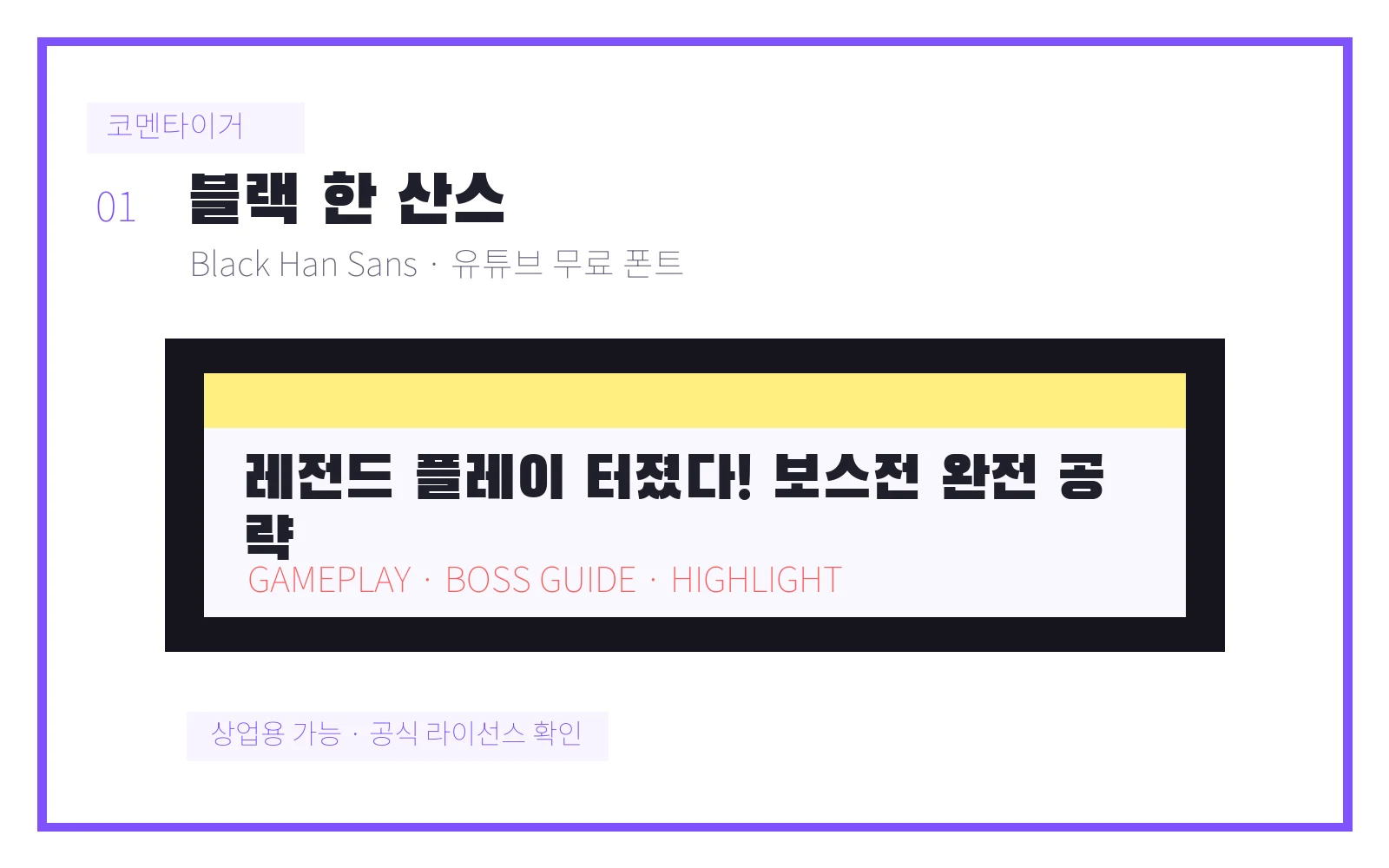
- 추천 용도: 강한 타격감이 있어 하이라이트 썸네일 제목에 좋습니다.
2. 도현
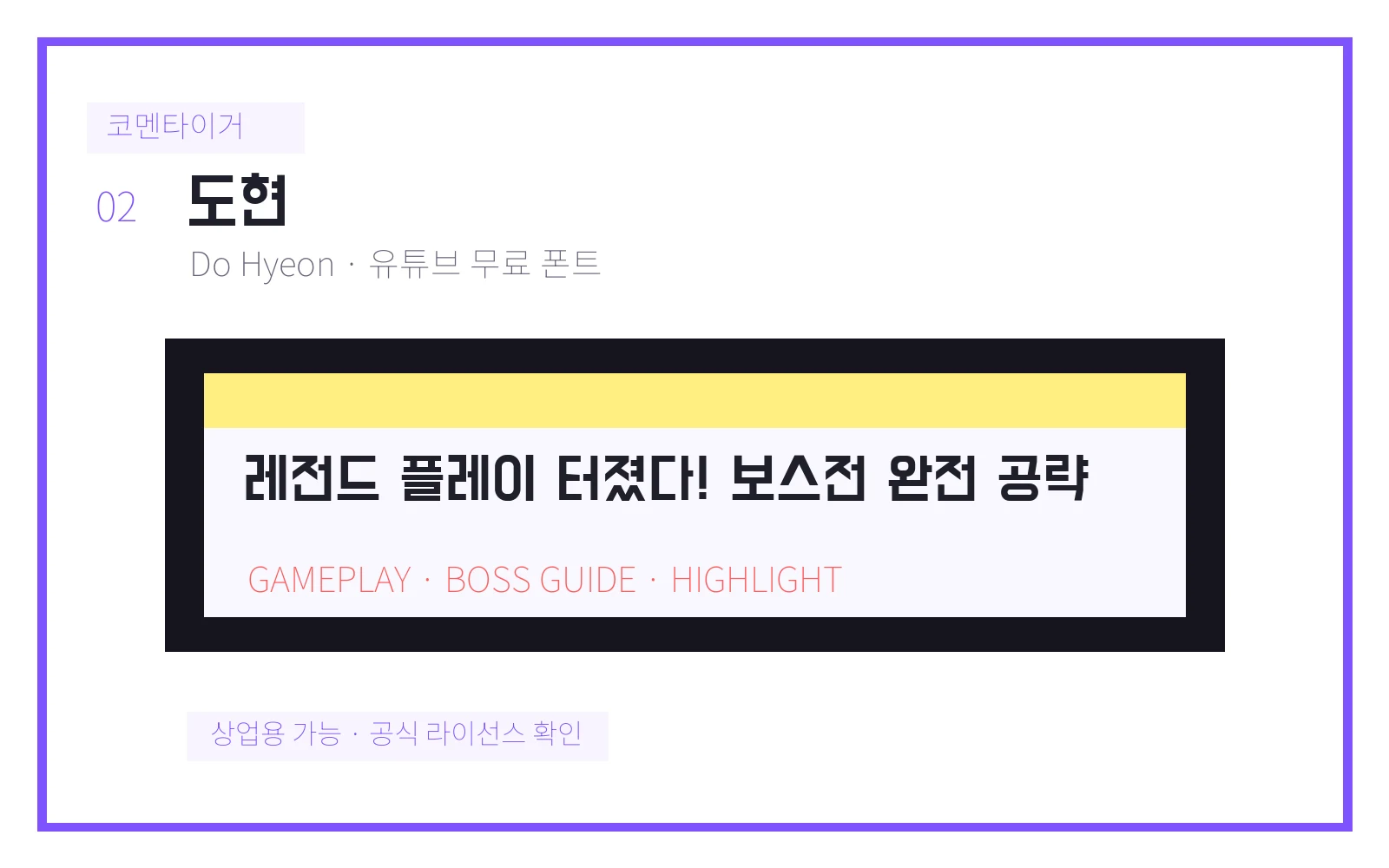
- 추천 용도: 공략, 리뷰, 티어표처럼 정보형 게임 영상에 잘 맞습니다.
3. 구기
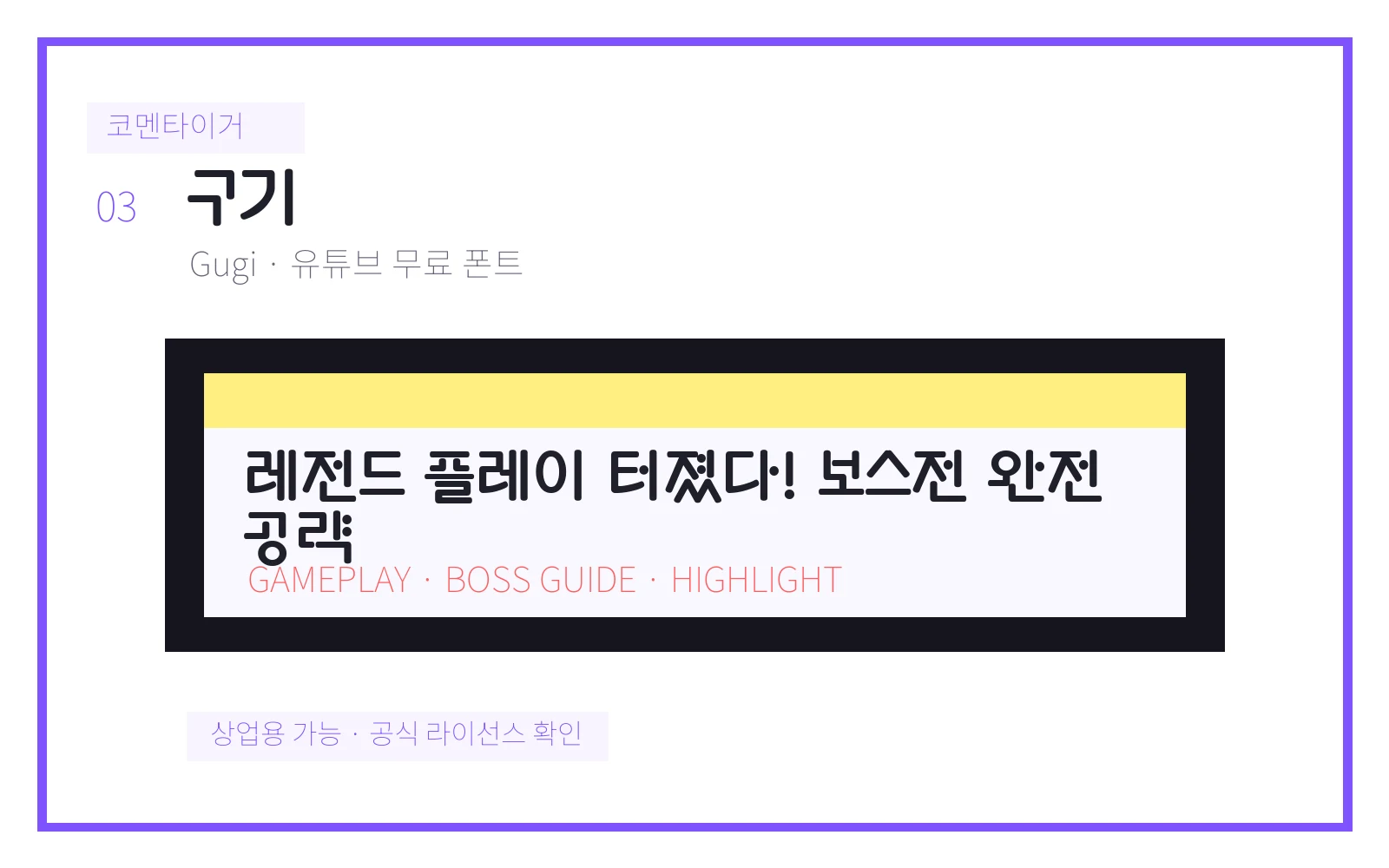
- 추천 용도: 게임 UI 같은 개성이 있어 포인트 문구에 쓰기 좋습니다.
4. 베이글 팻 원
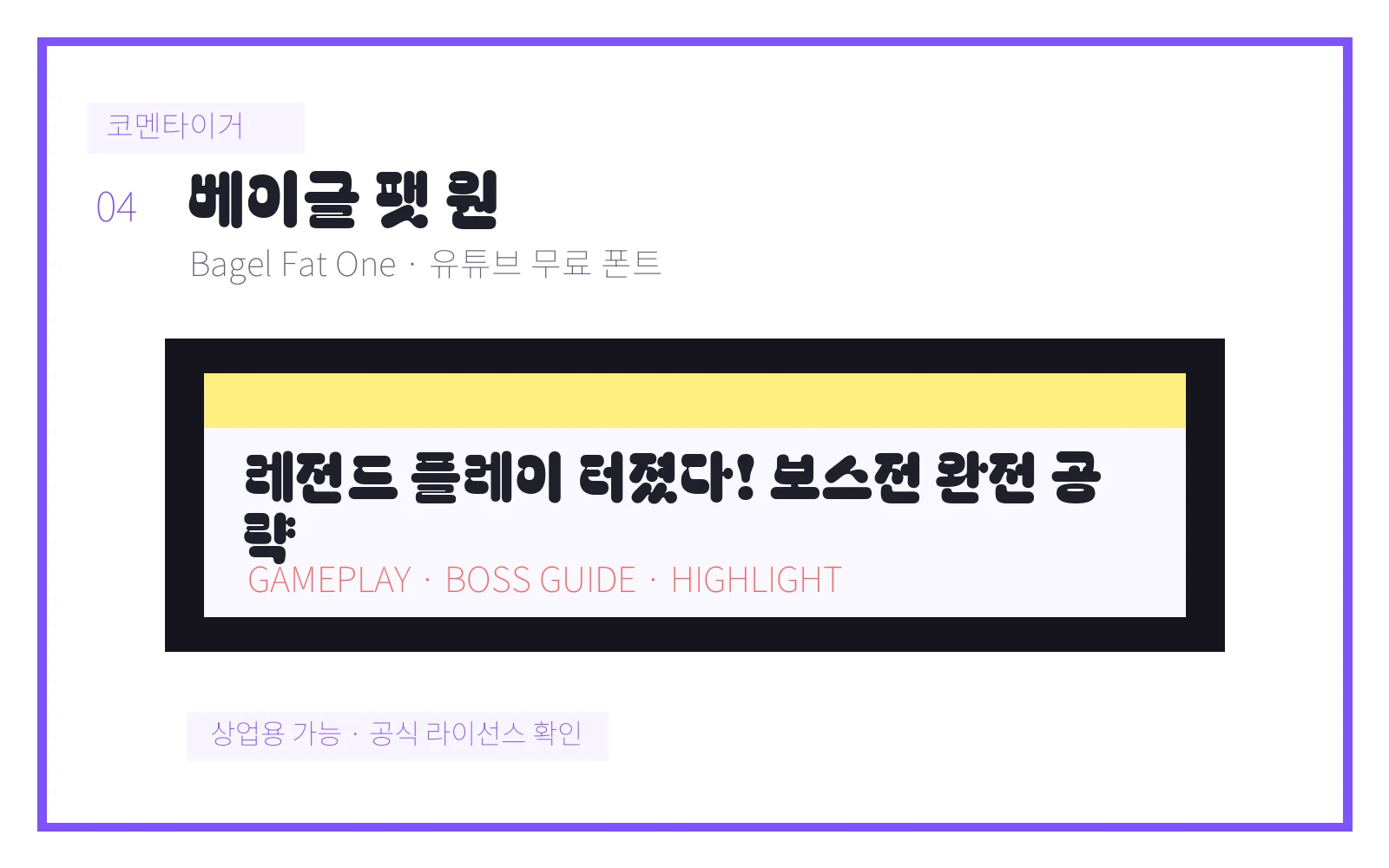
- 추천 용도: 캐주얼 게임이나 예능형 게임 영상에 어울립니다.
5. 동글
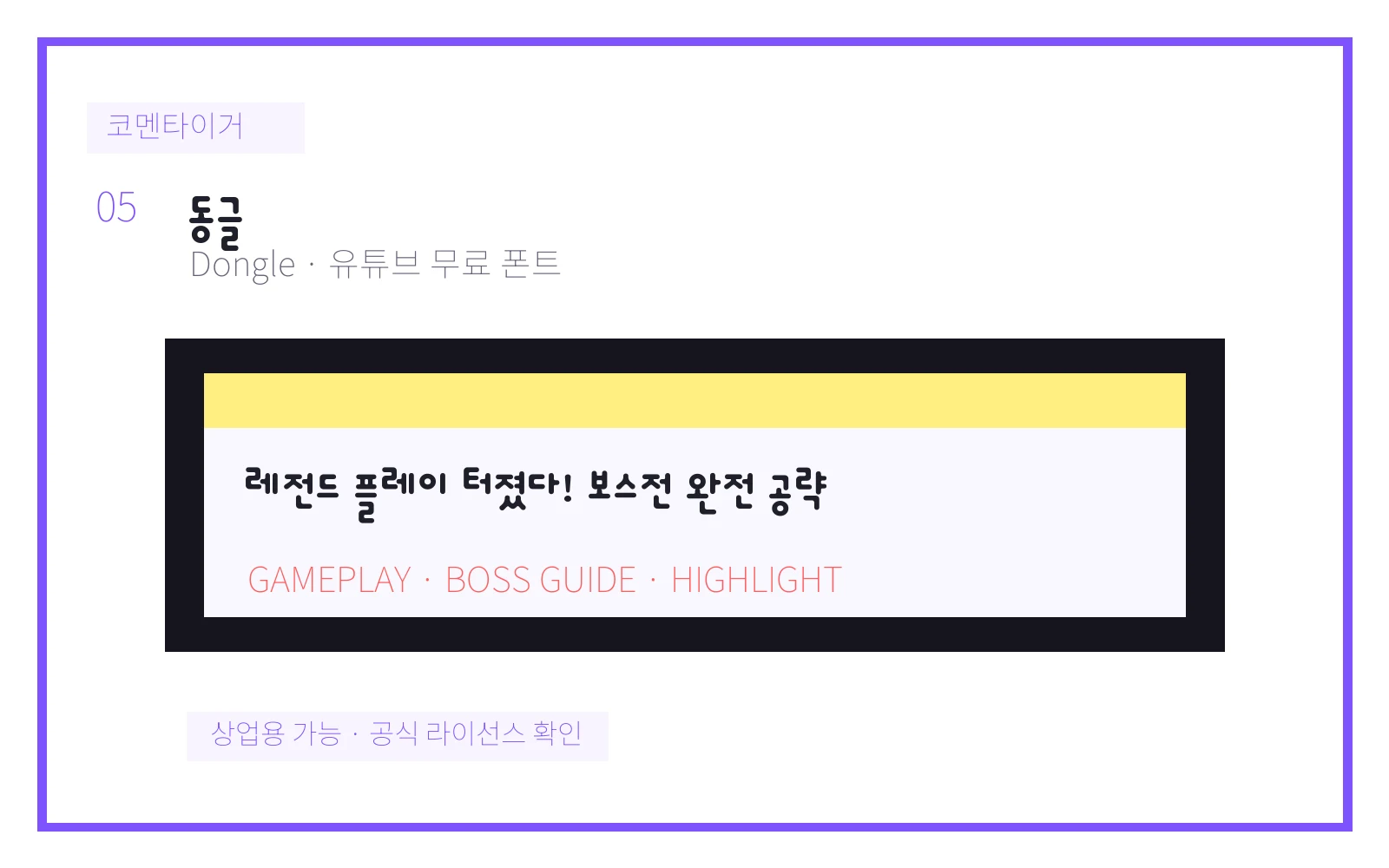
- 추천 용도: 큼직한 쇼츠 자막이나 리액션 문구에 쓰기 편합니다.
6. 주아
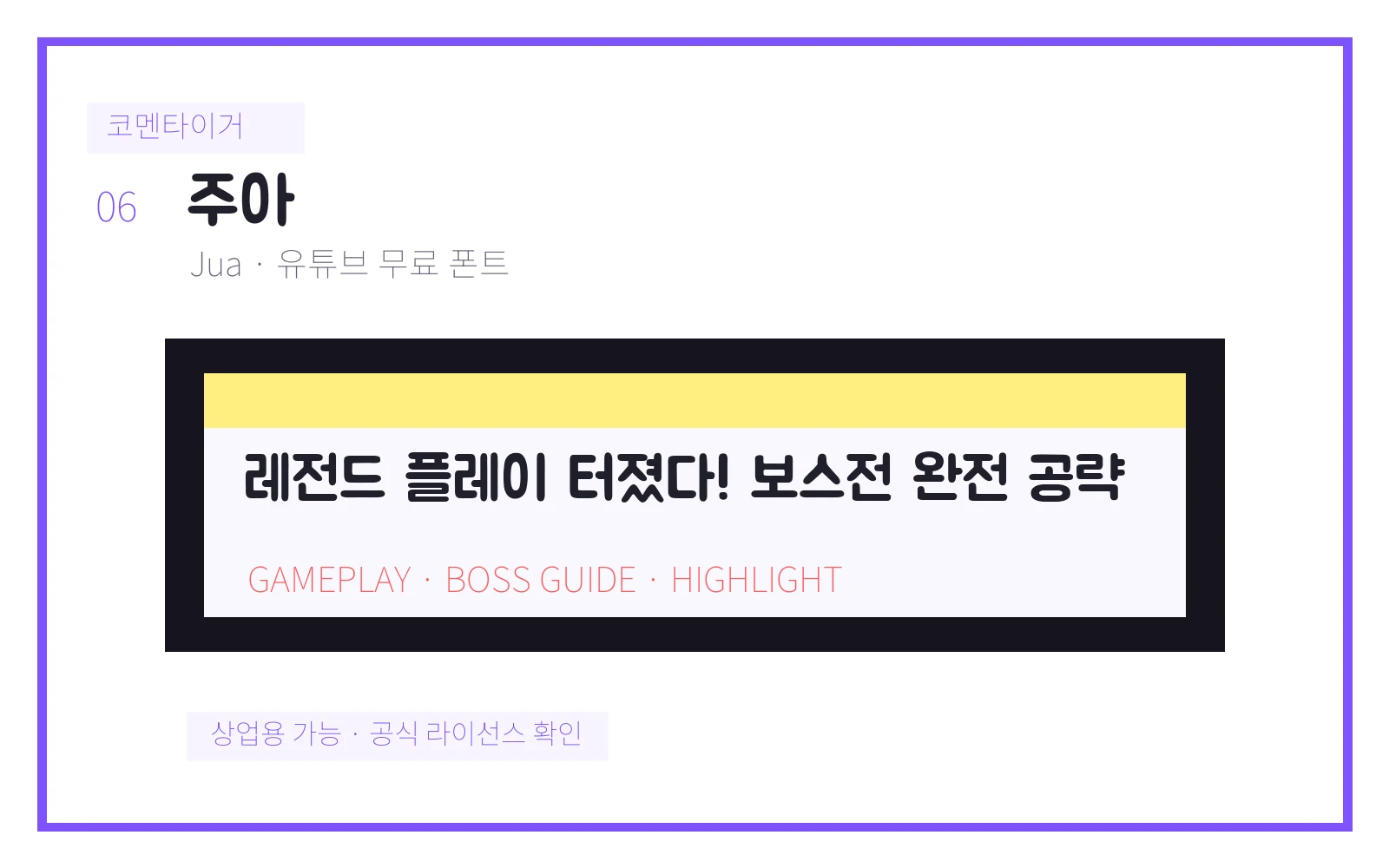
- 추천 용도: 친근한 인상이라 마인크래프트, 로블록스류 영상에도 무난합니다.
7. 독도
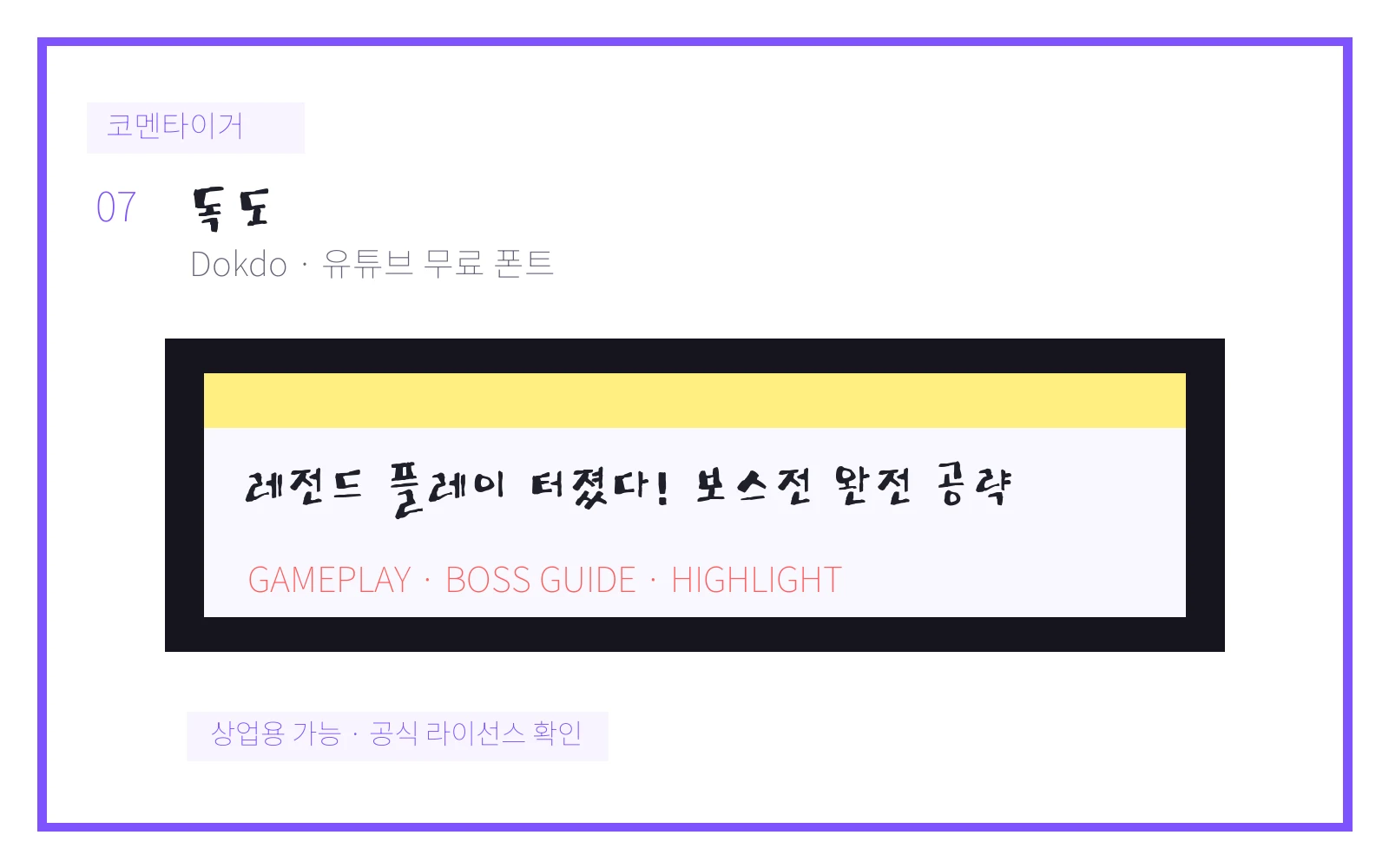
- 추천 용도: 거칠고 튀는 느낌이라 분노, 실패, 반전 문구에 잘 맞습니다.
8. 이스트 씨 독도
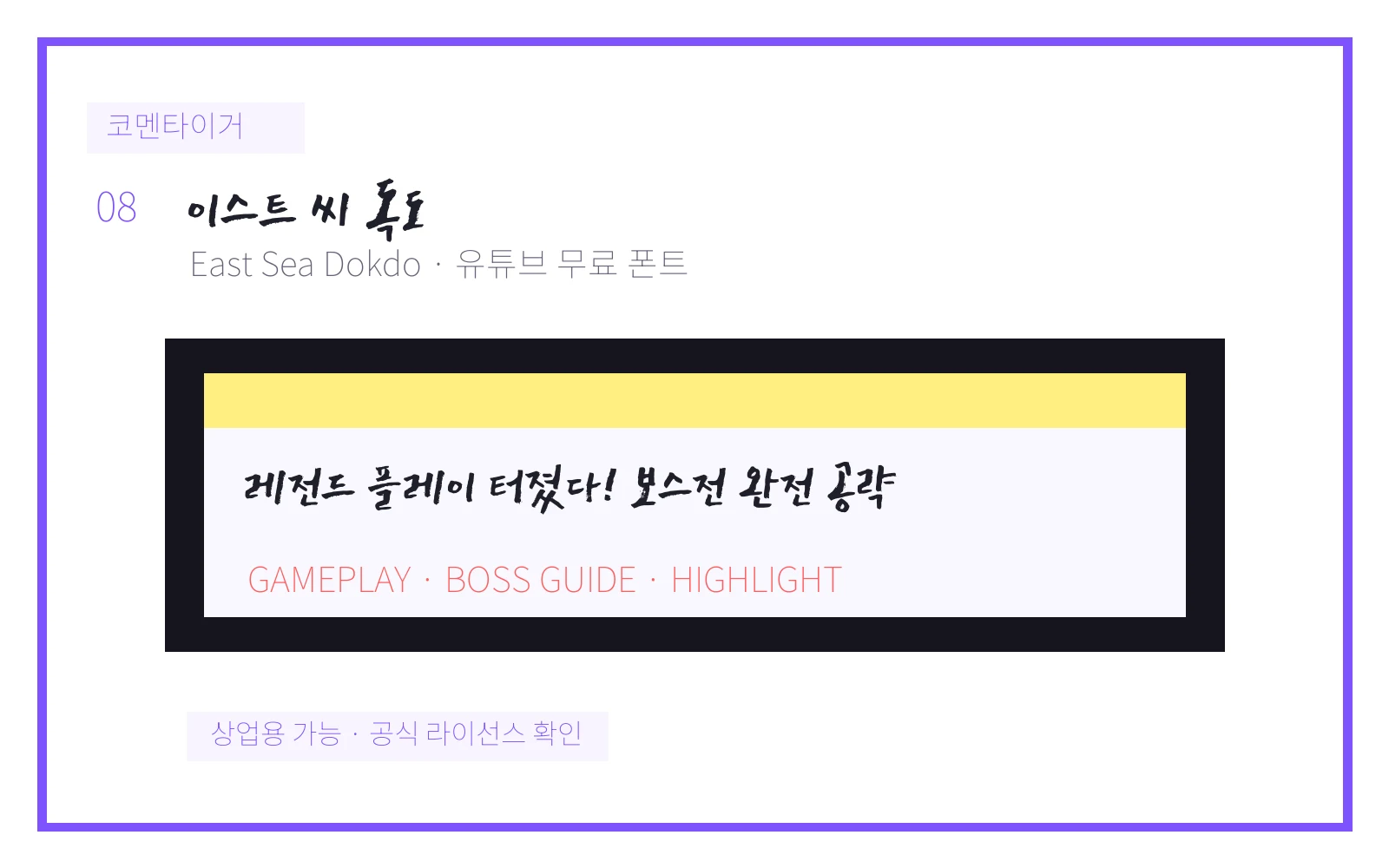
- 추천 용도: 강한 손맛이 있어 액션 게임 썸네일에 개성을 줍니다.
9. 키랑 해랑
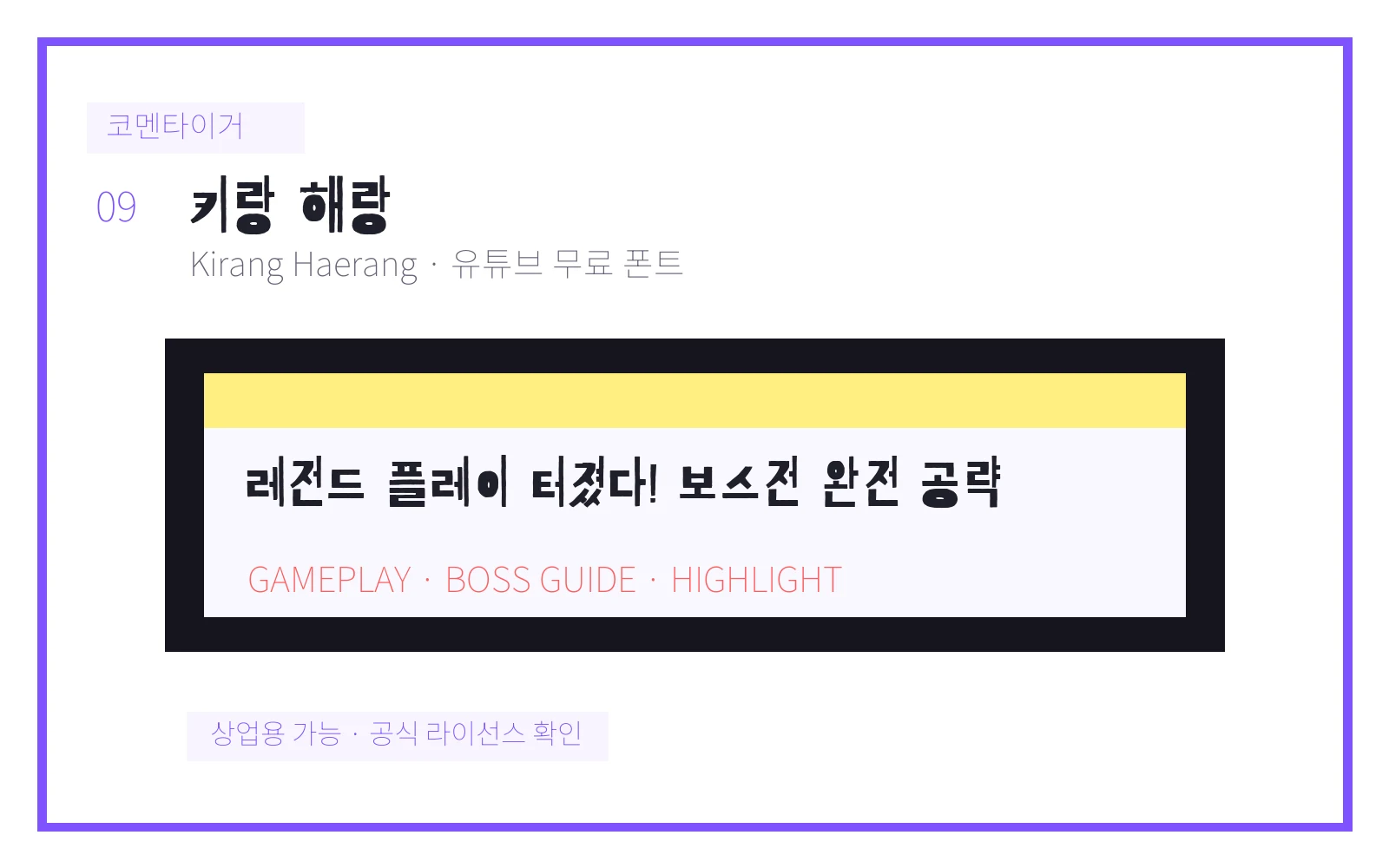
- 추천 용도: 장난스럽고 과장된 느낌이 있어 예능형 게임 자막에 좋습니다.
10. 함렛
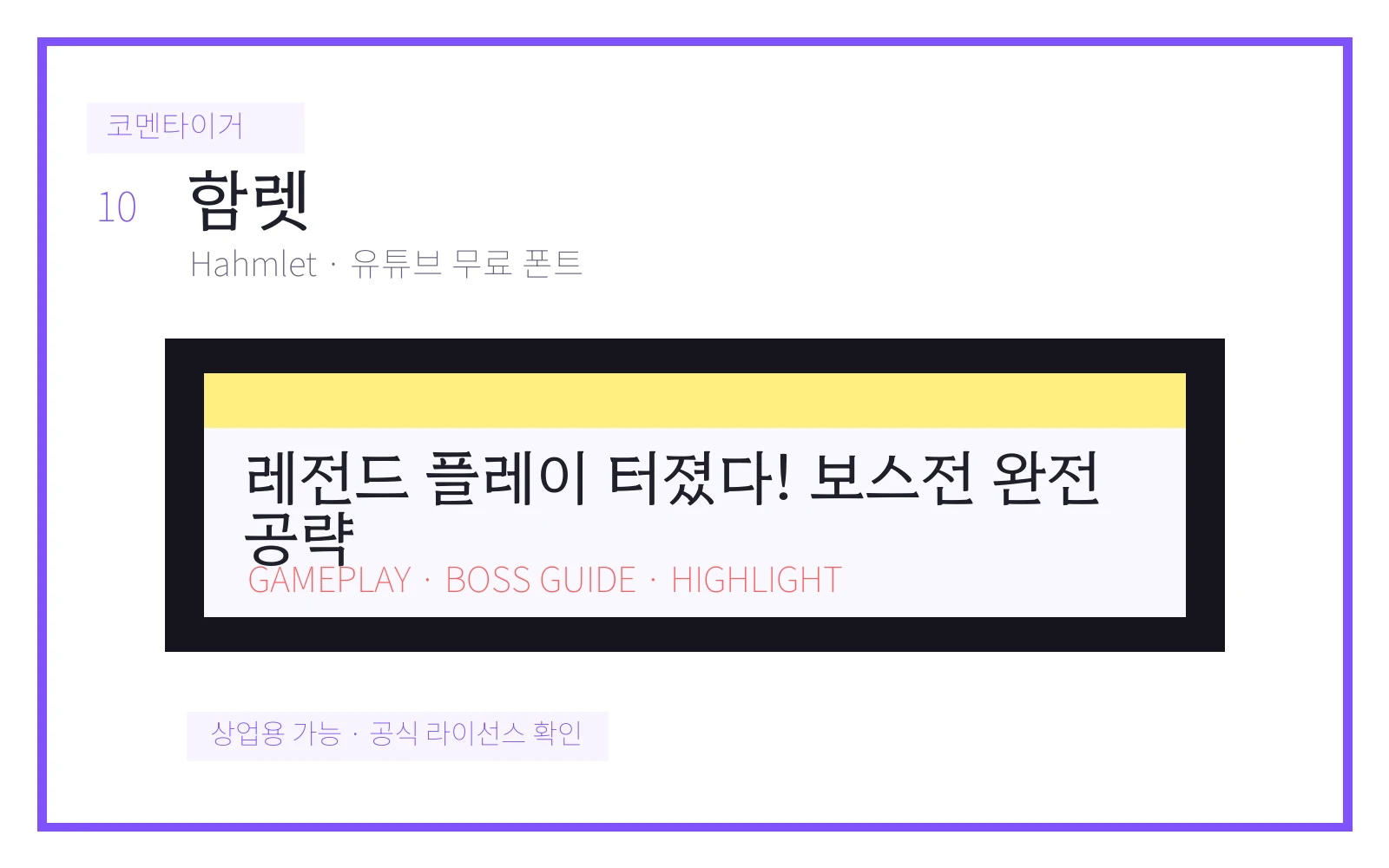
- 추천 용도: 게임 공략 문서형 영상의 설명 자막에 안정적입니다.
짧게 고르는 기준
- 하이라이트·리액션: Black Han Sans, Gugi, Dokdo
- 공략·티어표: Do Hyeon, Hahmlet
- 캐주얼 게임·예능 편집: Bagel Fat One, Dongle, Jua
썸네일용 폰트는 예쁘기만 해서는 부족합니다. 모바일 화면에서 1초 안에 읽히는지, 배경 이미지 위에서도 묻히지 않는지, 같은 채널 안에서 반복 사용해도 질리지 않는지를 같이 보는 편이 좋습니다.
용도별 추천 정리
- 하이라이트 썸네일: 블랙 한 산스, 도현, Gugi
- 밈·리액션 자막: 주아, 동글, 배글팻원
- 공략·정보형 영상: 노토 산스 KR, 함렛